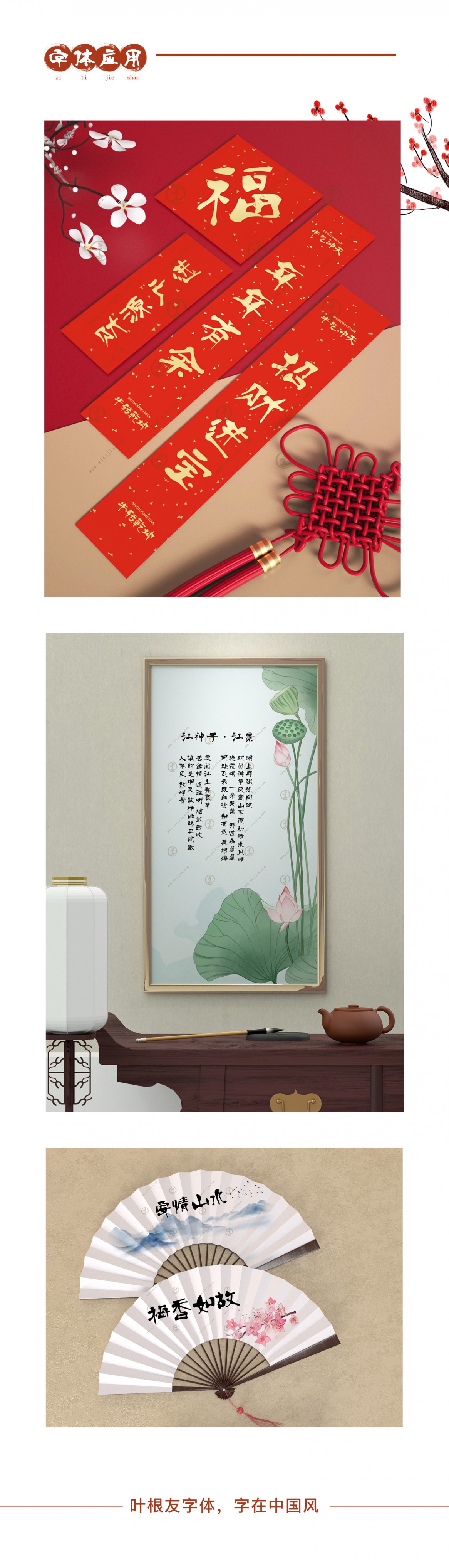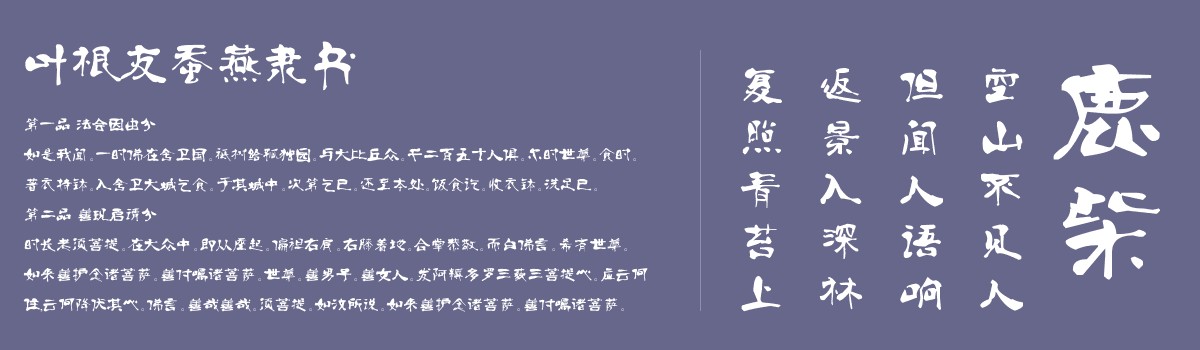
叶根友蚕燕隶书
创作年代:2008年
字体字数:6763个中文汉字以及其他英文字母和阿拉伯数字
字体介绍
叶根友蚕燕隶书是一款具有隶书的传统风格和现代书法之结合体创新字体,赋予字体内在的遒劲之美,圆润而富有质感,特点鲜明,让人看后过目不忘,为叶根友系列字体最受欢迎字型之一。将隶书的蚕头燕尾之风格包容于字里行间,用现代的创作思维去于古代书法对话,正所谓师古而不泥古,在叶根友认为,所有书法创新也好,创作也罢,均是建立在古人的肩膀上去思考,但是不能一味的去模仿古人,而是要有自己的风格特征,正如这款叶根友蚕燕隶书字体作品而言,每个字的起笔和运笔都流露出一种书写者当时的真实心境,这款字体是在江苏常州创作的,历史四个月的书写过程,每次写完不满意的一律扔掉,前后大约有些字写了八到十次之多。